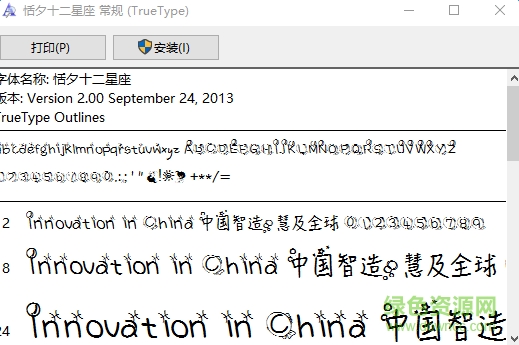
十二星座泡泡魚字體是一款很特殊的電腦個性字體,這款字體寫出來的字不像普通字體那樣就是很規(guī)范的,就像這款字體的名字一樣,在寫出來的字體上面是會有泡泡的裝飾的,是不是很可愛呢,喜歡的朋友就快來綠色資源網(wǎng)下載吧。
十二星座泡泡魚字體是一款很受年輕朋友們喜歡的電腦藝術(shù)字體,因為這款字體寫出來的字特別好看、有魅力,如果你也喜歡這款字體就快來綠色資源網(wǎng)下載吧。